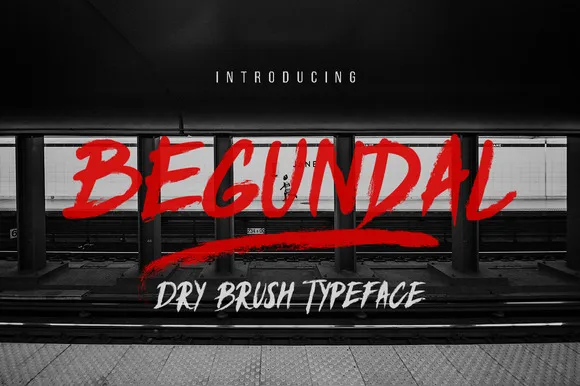
Begundal Brush Font – Download Grátis
Begundal é uma fonte brush script que transmite energia e originalidade com sua mão-dura escrita a lápis de carbono. Ideal para diversos usos, essa elegante tipografia é perfeita para aplicar na criação de logotipos, desenhos de badges ou insignias, embalagens, cartazes, capas de mangá e até mesmo convites de casamento. A sua estética fresca e moderna torna-a uma escolha ótima para criar um tom agradável em design editorial, seja para as etiquetas de água na sua loja do shopping ou para aqueles cartões de apelo direto que você deseja imprimir na sua nova empresa. Através deste charco de escrita, deixe o seu toque único se expressar. Com Begundal Script Font, suas criações ganharão um brilho especial e uma cara moderna. Que tal experimentar agora? Se estiver pronto para explorar novos horizontes no design editorial ou na tipografia, comece por aqui com Begundal. Terá um ótimo dia!